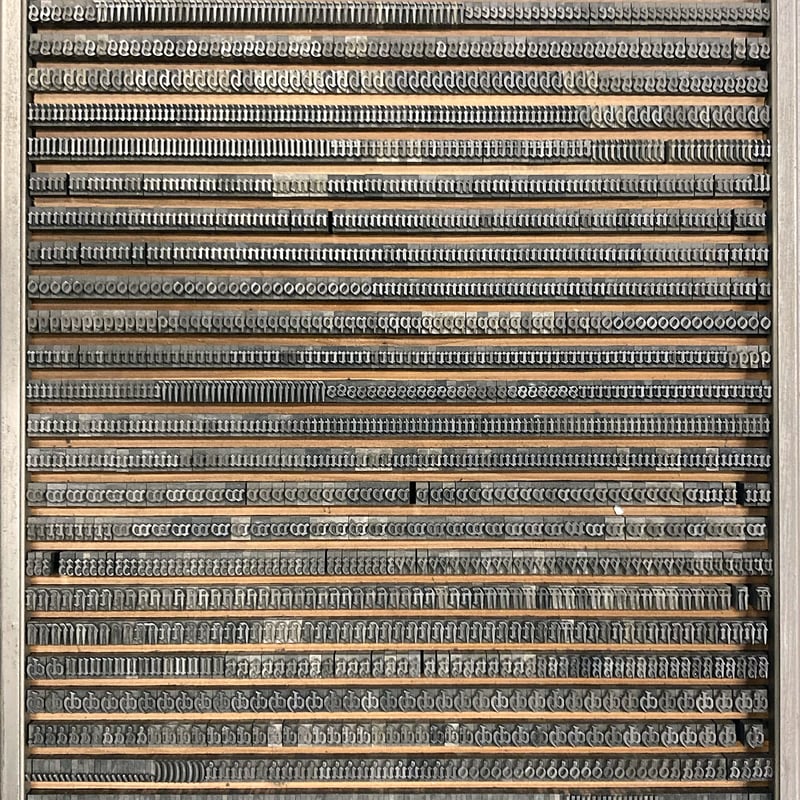
Schwabacher
Grösse: 36 pt
Druckmuster mit Text «Nuernberger Schwabacher, Johann Wilhelm Haas, 36pt»
Klassifizierung
Blackletter
Grösse
36 pt / 3 c
Design
Edmund Thiele
Jahr
1927
Schriftgiesserei
Haas
Entspricht nicht exakt der Nürnberger Schwabacher, aber ist sehr ähnlich (Abweichungen bei N, a, g).